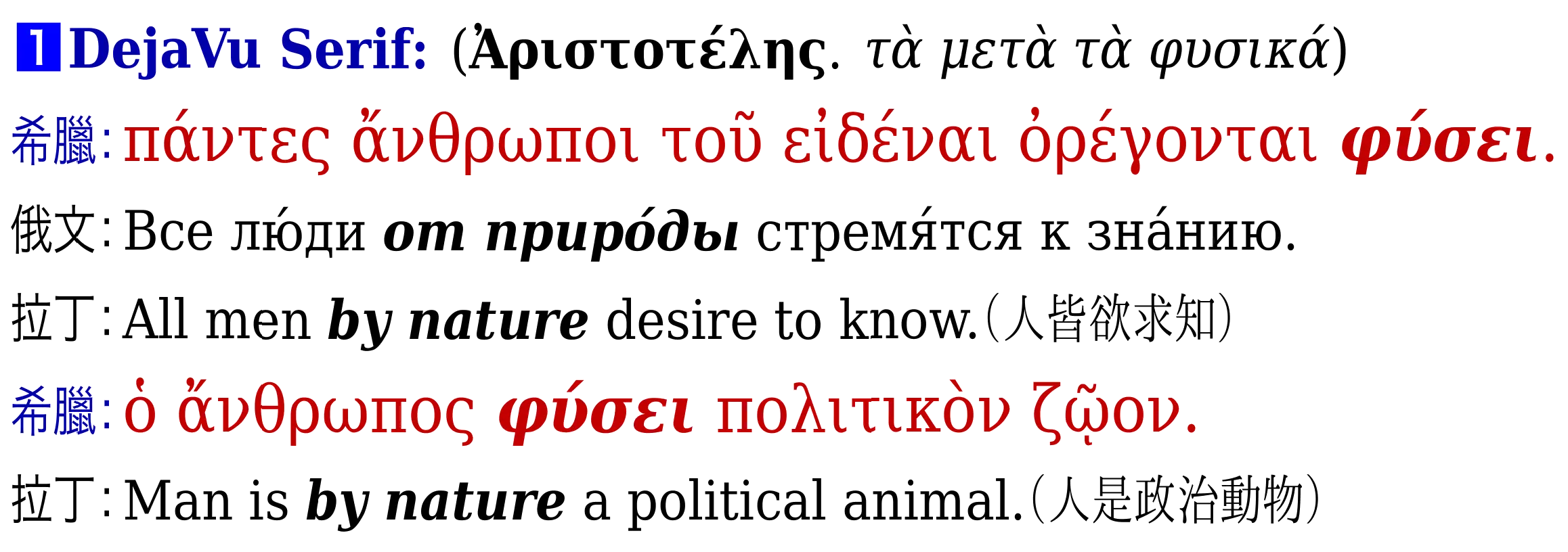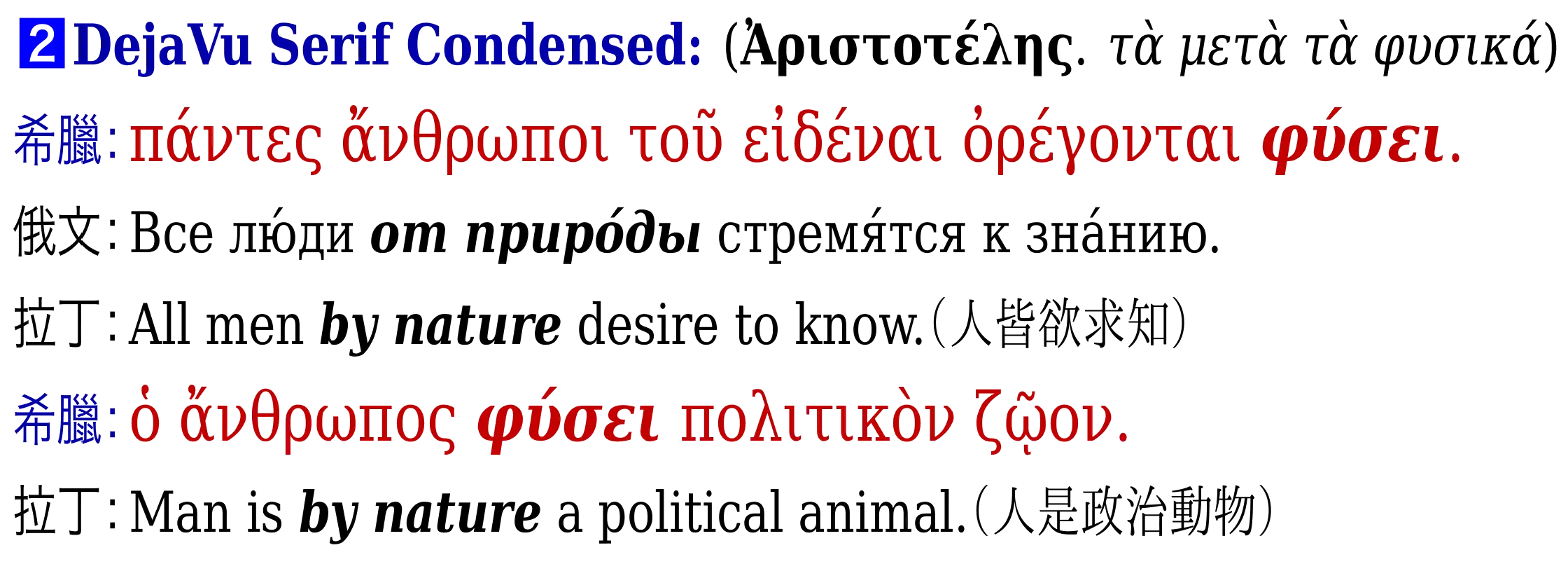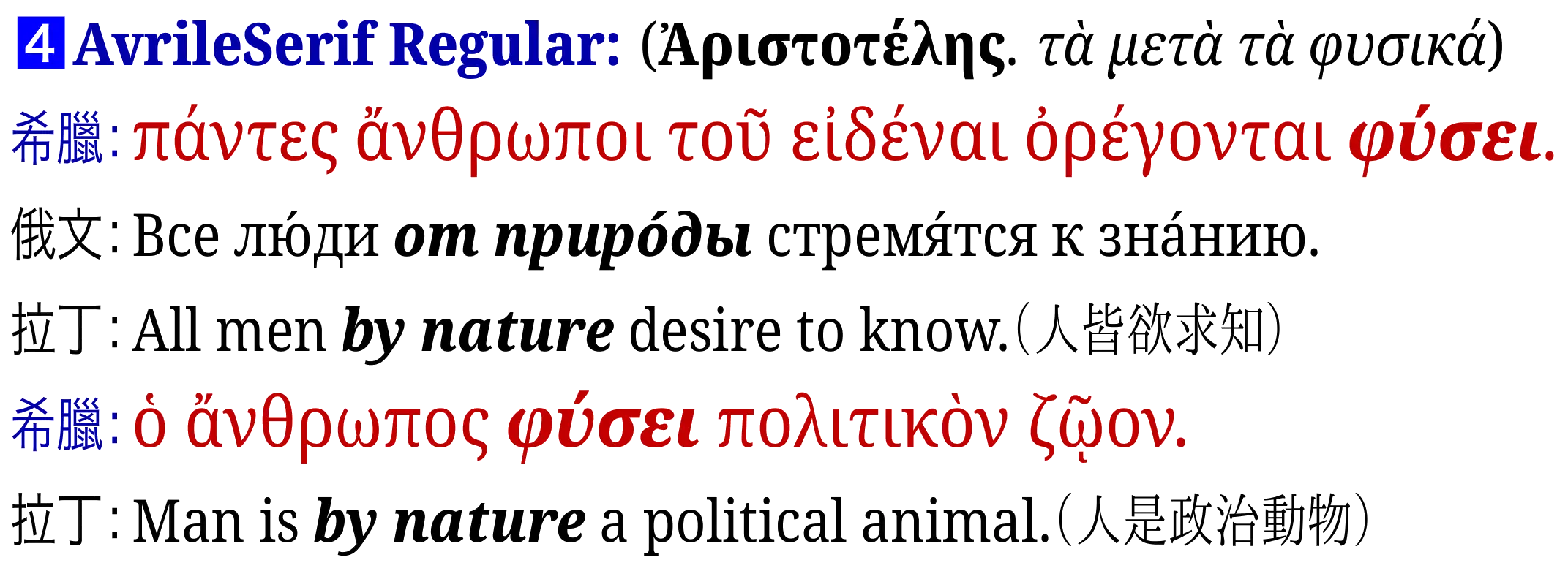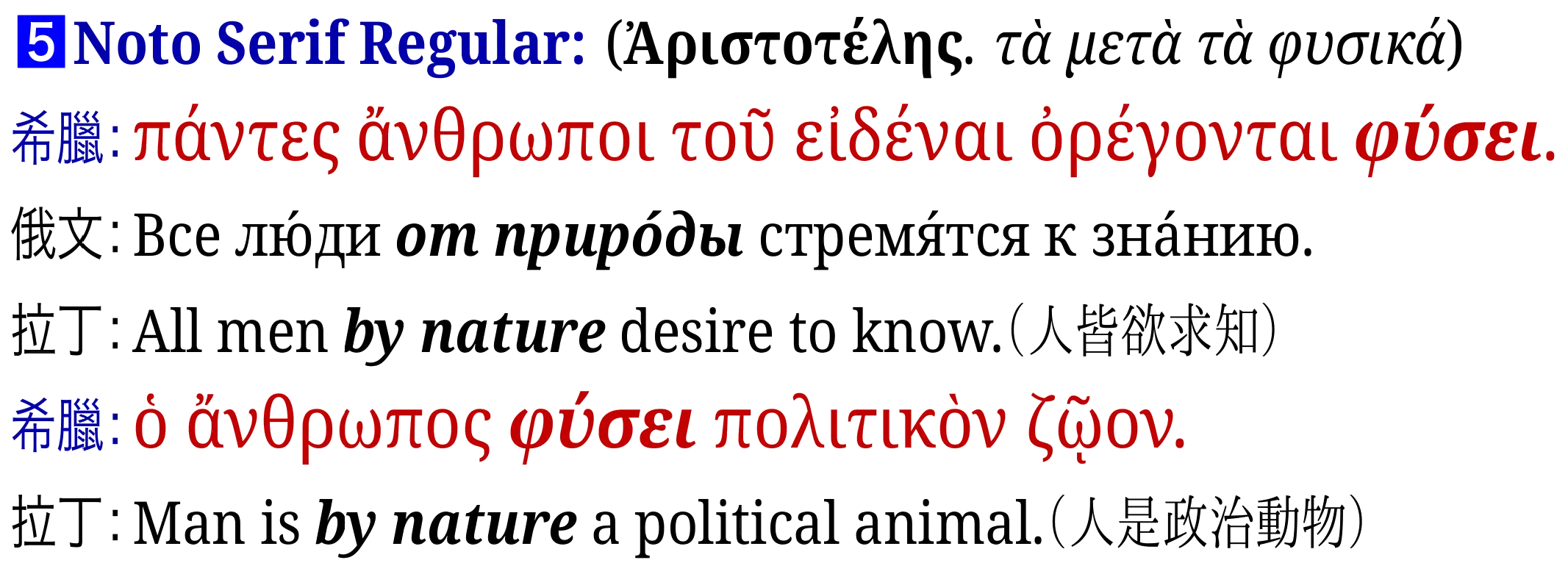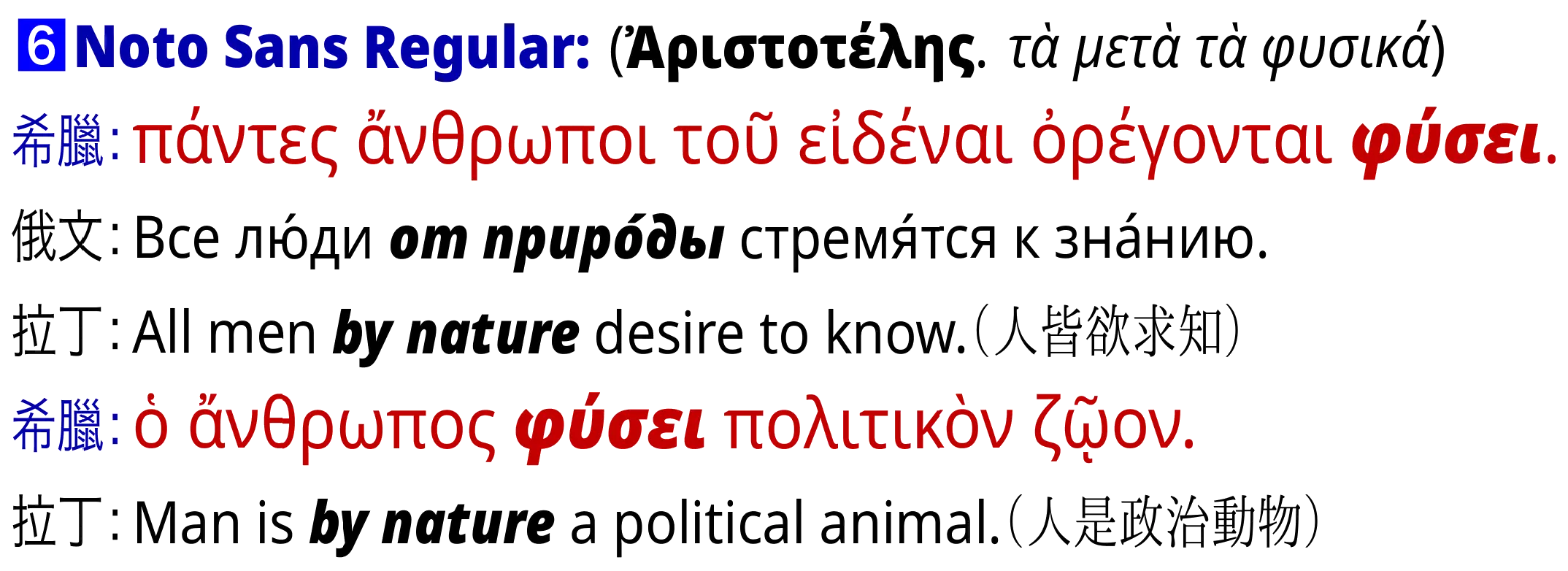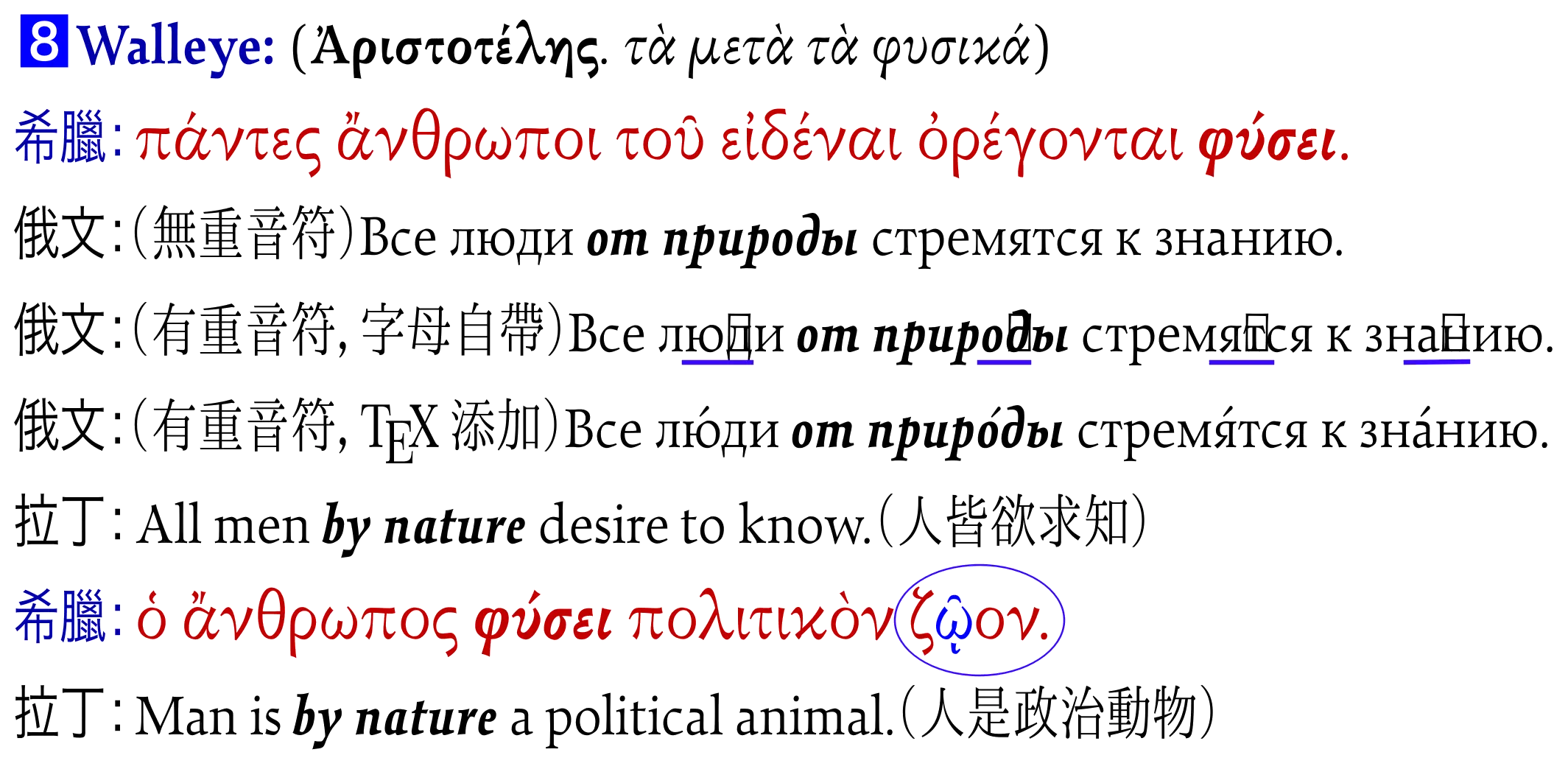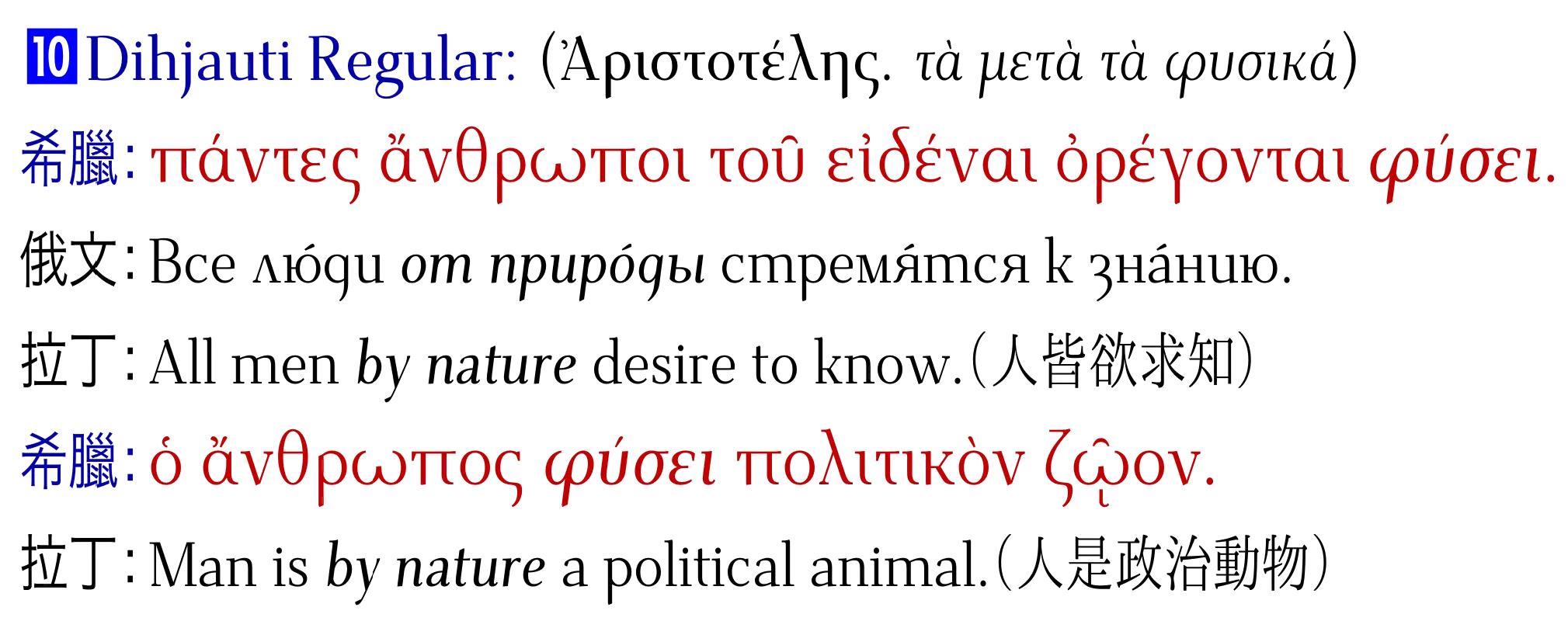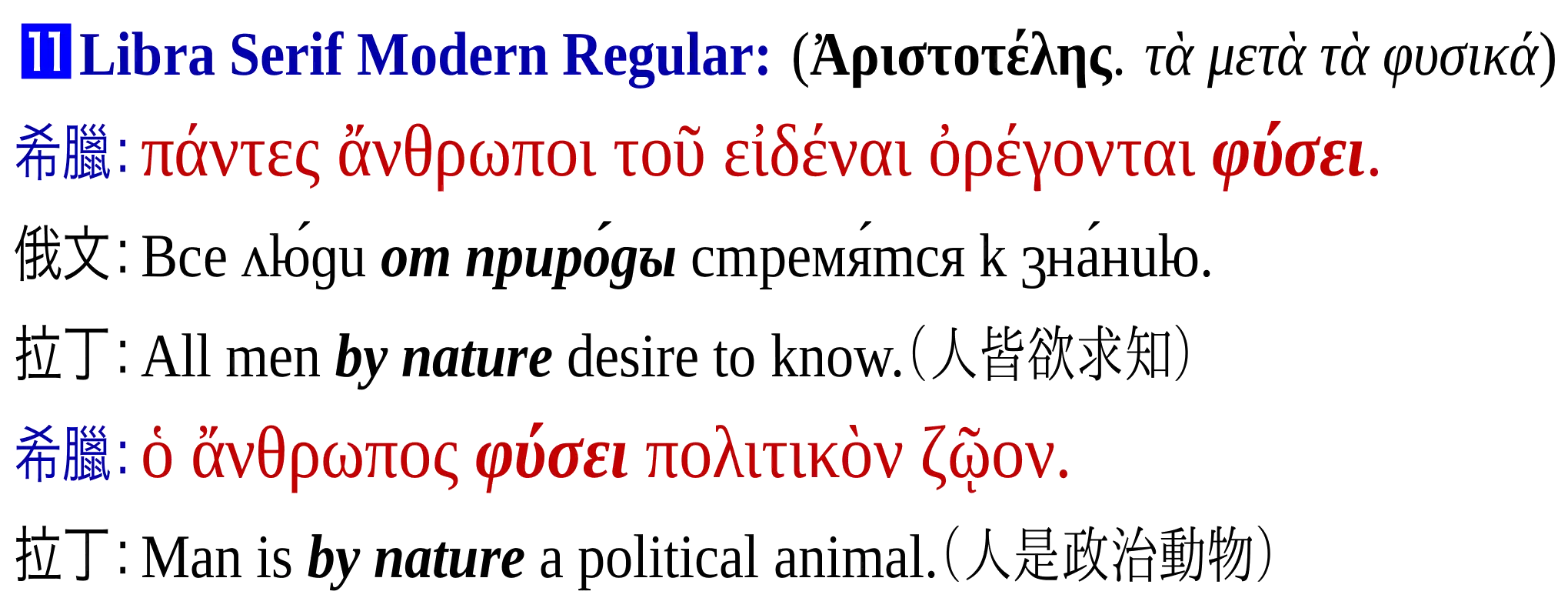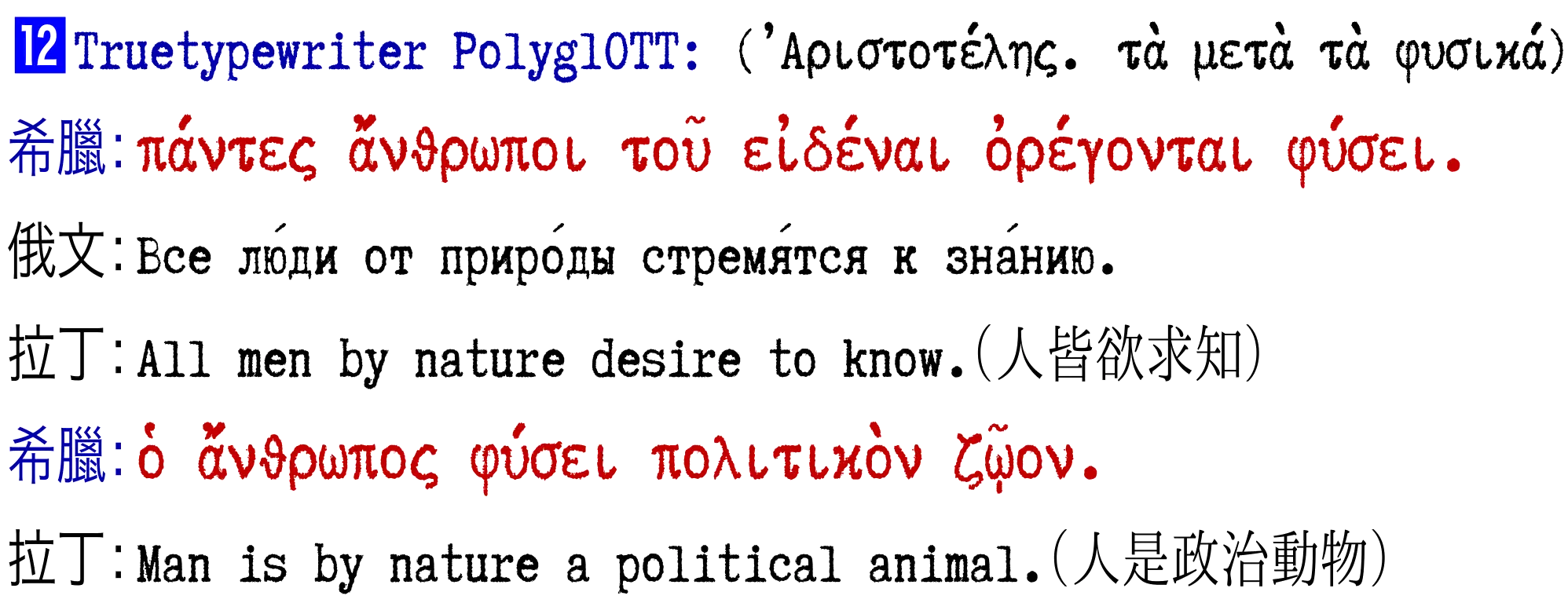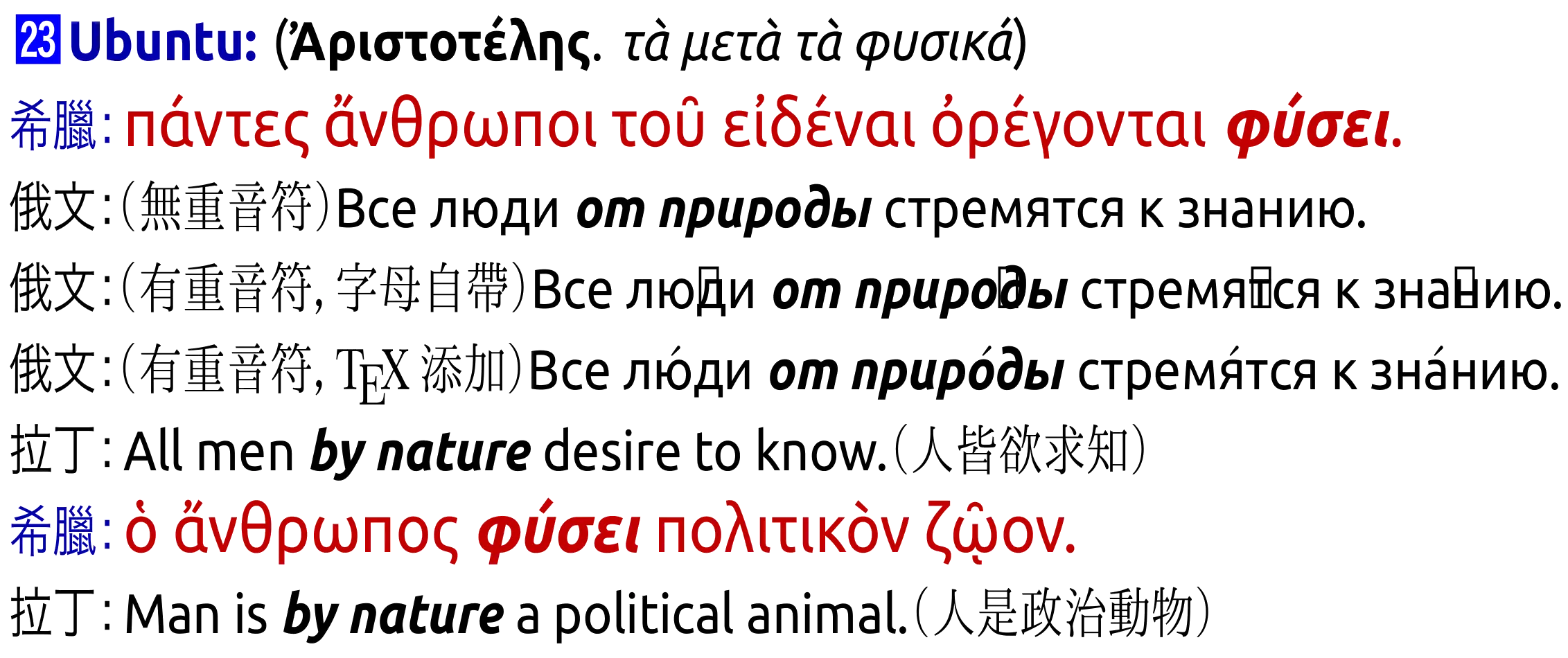
此前整理邏輯學材料,需要用希臘字母抽象替代某些對象時都是以 TeX 命令實現。近來折騰通史材料,常常遇到古希臘人名與書名,難以用 TeX 命令逐個字母輸入,需要尋找支持希臘文排版的字型。經過幾天的蒐羅、測試、比對,發覺下列二十多種字型大體上可滿足古希臘文獻的排版。本文以下面兩句話及其對應的英、俄譯文簡單測試各字型的版式效果。
πάντες (求知是人的本性)ἄνθρωποι τοῦ εἰδέναι ὀρέγονταιφύσει .ὁ ἄνθρωπος (人天生是政治動物)φύσει πολιτικὸν ζῷον.
πάντες ἄνθρωποι τοῦ εἰδέναι ὀρέγονταιφύσει .ὁ ἄνθρωπος φύσει πολιτικὸν ζῷον.
結論〔info〕
Walleye 與 Brill 難分伯仲,混排時優先使用。其餘系列字體如 Tinos、Avrile Serif、DejaVu Serif、Cambria 等亦適於跨語種混排。若要爲不同字母設置不同字體混用,則希臘字母排版字體可選種類就更多。
以下僅就作者所掌握的材料,對可選字體樣式略加介紹。
DejaVu Serif
- 字型風格: DejaVu Serif 是較常見的字型,字符筆劃風格較傳統,個人感覺欠缺靈動,略顯死板。
- 字重樣式: 字重、樣式較齊全,粗體、斜體、粗斜體等支持較全面。斜體樣式較怪異。
- 俄文支持: 對自帶重音符的西里爾字母支持較好。若俄文與古希臘文混排,不必單獨設定各自材料的字體樣式。
DejaVu Serif Condensed
- 與前款字型屬於同一系列,惟字符寬度壓縮了(Condensed)一些。
EB Garamond
- 字型風格: Garamond 也是較常見的字型,希臘、西里爾、拉丁字母的樣式設計都很美觀,筆畫細節邊角或收尾彰顯靈動,不死板。
- 字重樣式: 字重、樣式較齊全,粗體、斜體、粗斜體等支持較全面。斜體風格既統一又能有明顯的變化。
- 俄文支持: 對自帶重音符的西里爾字母支持略有瑕疵,重音符位置詭異,即使以 TeX 命令
л\'юди添加重音符,其位置亦詭異。若俄文與古希臘文混排,不必單獨設定各自材料的字體樣式。
Avrile Serif
- 字型風格: 對 Avrile Serif 字型較陌生,總體不太喜歡其設計風格。希臘、西里爾、拉丁字母的樣式設計似乎談不上莊重,卻略顯笨重。
- 字重樣式: 字重、樣式較齊全,粗體、斜體、粗斜體等支持較全面。
- 俄文支持: 對自帶重音符的西里爾字母支持較好。若俄文與古希臘文混排,不必單獨設定各自材料的字體樣式。
Noto Serif
- 字型風格: Noto Serif 是 Google 的開源字型,旨在「No Tofu」,消除因系統默認字型缺失而導致的豆腐塊顯示。這個系列字體支持的語言最全面,好像更多用於計算機系統界面的字符顯示。字符筆劃風格長得很像上面的 Avrile Serif,令人難以區分二者,不知二者有無承繼關係。印刷視覺效果未測試。
- 字重樣式: 字重、樣式較齊全,粗體、斜體、粗斜體等支持較全面。
- 俄文支持: 對自帶重音符的西里爾字母支持較好。若俄文與古希臘文混排,不必單獨設定各自材料的字體樣式。
Noto Sans
- 與前款字型屬於同一系列,前款屬於襯線字體,這個是對應的無襯線字型。用於顯示屏的效果不錯,印刷視覺效果未測試。支持希臘文的無襯線字體似乎不多,尤其是像這樣樣式、字重齊全的似乎更少。
Tinos
- 字型風格: 對 Tinos 字型較陌生,總體較喜歡其設計風格。希臘、西里爾、拉丁字母的樣式設計似乎都顯得嚴肅些,莊重而不笨重。字符筆畫收尾樣式很有特色。
- 字重樣式: 字重、樣式較齊全,粗體、斜體、粗斜體等支持較全面。斜體風格既統一又有變化。
- 俄文支持: 對自帶重音符的西里爾字母支持較好。若俄文與古希臘文混排,不必單獨設定各自材料的字體樣式。
- 有支持網頁使用的 Google Fonts 版本。
Walleye
- 字型風格: 對 Walleye 字型較陌生,至今所見最喜歡的字型。希臘、西里爾、拉丁字母的樣式設計似乎都顯得靈動而不輕浮,觀感靈動之餘又能感受到些許莊嚴。希臘字符筆畫收尾樣式峭拔而不尖刻,乾淨利索,流暢飄逸,很有特色。印刷之外,用於屏幕顯示的效果也很好。希臘字母的長音符或揚抑符樣式是短弧而非浪線(見
ζῷον ),與多數字體不同。 - 字重樣式: 字重、樣式較齊全,粗體、斜體、粗斜體等支持較全面。斜體風格既統一又有變化。
- 俄文支持: 對自帶重音符的西里爾字母支持略有瑕疵,重音符位置詭異,但是以 TeX 命令
л\'юди添加重音符,可得到正確的輸出樣式。若俄文與古希臘文混排,不必單獨設定各自材料的字體樣式。
καὶ τῶν ἐπιστημῶν δὲ τὴν αὑτῆς ἕνεκεν καὶ τοῦ εἰδέναι χάριν αἱρετὴν οὖσαν μᾶλλον εἶναι σοφίαν ἢ τὴν τῶν ἀποβαινόντων ἕνεκεν, καὶ τὴν ἀρχικωτέραν τῆς ὑπηρετούσης μᾶλλον σοφίαν… among the sciences we consider that that science which is desirable in itself and for the sake of knowledge is more nearly Wisdom than that which is desirable for its results… From Aristotle’s Metaphysics
Gentium
- 字型風格: 希臘、拉丁字母的樣式設計風格獨特,討人喜歡。
- 字重樣式: 只有一種字重,有對應的斜體,沒有對應的粗體。斜體風格變化不明顯,有時肉眼難以區分。(補註:Google Fonts上有一款 Gentium Plus 字型與 Gentium Book Plus 字型,包含 400、700 兩種字重與斜體樣式)
- 俄文支持: 缺少若干西里爾常用字母,用於俄文與古希臘文混排時需要單獨設定其他字型,版面風格未必容易統一。
Dihjauti
- 字型風格: 沒有考證這個字體的出處國度,但是看名字和字型筆畫都頗具南亞風情,猜測其當是出自有南亞背景的設計者,或其原初設計意圖是排版其他語言。
- 字重樣式: 字重、樣式較齊全,粗體、斜體、粗斜體等支持較全面。斜體風格既統一又有變化。
- 俄文支持: 對自帶重音符的西里爾字母支持較好,只是有些西里爾字母風格似乎顯得過於古老,像18世紀印刷物上的字體。
Libra Serif Modern
- 字型風格: 希臘、拉丁字母的樣式設計中規中矩,四平八穩。
- 字重樣式: 字重、樣式較齊全,粗體、斜體、粗斜體等支持較全面。斜體風格既統一又有變化。
- 俄文支持: 對自帶重音符的西里爾字母支持略有瑕疵,重音符位置詭異。只是有些西里爾字母風格似乎顯得詭異,像18世紀印刷物上的字體。
Truetypewriter PolyglOTT
- 字型風格: 坊間有不少這種打字機風格的字體,類似地,也有不少仿製刻版書風格的中文字型。這款字型對希臘文支持較好,各種音符都大致能正常顯示。
- 字重樣式: 無粗體、斜體。
- 俄文支持: 對自帶重音符的西里爾字母支持略有瑕疵,重音符位置詭異。
GFS Neohellenic
- 字型風格: 字符筆畫兼具襯線與無襯線樣式,似乎是介於襯線與無襯線之間的字型,較獨特。
- 字重樣式: 字重、樣式較齊全,粗體、斜體、粗斜體等支持較全面。
- 俄文支持: 不特別設定其他字型的化,西里爾字母輸出的是豆腐塊。若用於俄文與古希臘文混排時需要單獨設定其他字型,版面風格未必容易統一。
Kalypsa Medium
- 字型風格: 另一種無襯線字型,中規中矩。希臘字母的長音符或揚抑符樣式是短弧而非浪線(見
ζῷον ),與多數字體不同。 - 字重樣式: 只有一個 Medium 字重。沒有對應的粗體、斜體、粗斜體。
- 俄文支持: 對自帶重音符的西里爾字母支持較好。
New Athena Unicode
- 字型風格: 希臘字型有印章或舊書複印的風格,筆端襯線不明顯。拉丁、西里爾字母樣式中規中矩,與對應的希臘字母風格不統一。
- 字重樣式: 只有一個字重。沒有對應的粗體、斜體、粗斜體。
- 俄文支持: 對自帶重音符的西里爾字母支持較好。
Tantular
- 字型風格: 沒有考證這個字體的出處國度,但是看名字,猜測其當是出自有南亞或中亞背景的設計者,或其原初設計意圖是排版其他語言。爲數不多的無襯線字體。
- 字重樣式: 可惜只有一個字重。沒有對應的粗體、斜體、粗斜體。
- 俄文支持: 對自帶重音符的西里爾字母支持尚可,重音符位置有些許詭異。
Quivira
- 字型風格: 希臘、西里爾、拉丁字母的樣式設計似乎都顯得莊重多於靈動。
- 字重樣式: 只有一個字重。沒有對應的粗體、斜體、粗斜體。
- 俄文支持: 對自帶重音符的西里爾字母支持較好。
Theano Modern
- 字型風格: 看字體名稱,上述兩款屬於當屬於同一系列,一個是「Modern」一個是「Old Style」。就希臘字母樣式而言,個人更喜歡 Theano OldStyle.
- 字重樣式: 可惜只有一個字重。沒有對應的粗體、斜體、粗斜體。
- 俄文支持: 不支持。
Theano OldStyle
- 與前列字型應是一個體系。
Foulis Greek
- 字型風格: 看起來非常靈動的希臘文字型,拉丁字符的筆畫末端風格也很獨特,與希臘字型一樣,都能顯示出流動感。
- 字重樣式: 可惜只有一個字重。沒有對應的粗體、斜體、粗斜體。
- 俄文支持: 不支持。
Galatia SIL
- 字型風格: 顯得有些胖,但似乎也不會令人覺得笨重、笨拙。希臘字母的長音符或揚抑符樣式是短弧而非浪線(見
ζῷον ),與多數字體不同。 - 字重樣式: 可惜只有一個字重。有對應的粗體,沒有對應的斜體。
- 俄文支持: 不支持。
GFS Didot Regular
- 字型風格: 看起來較厚重而不笨拙的字型,也略帶靈動感。
- 字重樣式: 只有一個字重。沒有對應的粗體、斜體、粗斜體。
- 俄文支持: 不支持。
Ubuntu
- 字型風格: Linux 系統常見的屏幕字體,對各種音符的支持較好,用於屏幕顯示很簡潔明了,用於印刷效果似乎不是很好。
- 字重樣式: 字重、樣式較齊全,粗體、斜體、粗斜體等支持較全面。
- 俄文支持: 對自帶重音符的西里爾字母支持有瑕疵,但是以 TeX 命令
л\'юди添加重音符,可得到正確的輸出樣式。若俄文與古希臘文混排,不必單獨設定各自材料的字體樣式。
Cambria
- 字型風格: Win 系統常見的排版數學材料的字體,對各種音符的支持較好,風格偏莊重些。
- 字重樣式: 字重、樣式較齊全,粗體、斜體、粗斜體等支持較全面。
- 俄文支持: 對自帶重音符的西里爾字母支持較好。若俄文與古希臘文混排,不必單獨設定各自材料的字體樣式。
Minion Pro
- 字型風格: 好像是 Adobe 家的,不知道能不能商用。拉丁、西里爾字母的字型纖細俊秀。
- 字重樣式: 字重、樣式較齊全,粗體、斜體、粗斜體等支持較全面。
- 俄文支持: 對自帶重音符的西里爾字母支持有瑕疵,但是以 TeX 命令
л\'юди添加重音符,可得到正確的輸出樣式。若俄文與古希臘文混排,不必單獨設定各自材料的字體樣式。
Arial
- 字型風格: 各種操作系統中最常見的無襯線顯示字體,對希臘、西里爾、拉丁字母的支持都中規中矩。
- 字重樣式: 字重、樣式較齊全,粗體、斜體、粗斜體等支持較全面。
Brill
- 字型風格: Brill出版社定製的專用字體,對希臘文、拉丁文、西里爾等支持較好,是標緻的無襯線風格,較完美。
- 字重樣式: 字重、樣式較齊全,粗體、斜體、粗斜體等支持較全面。但希臘字母對應的粗體視覺上不夠突出,或不易分辨是否加粗。
- 俄文支持: 很好,跨語種混排樣式很美觀。